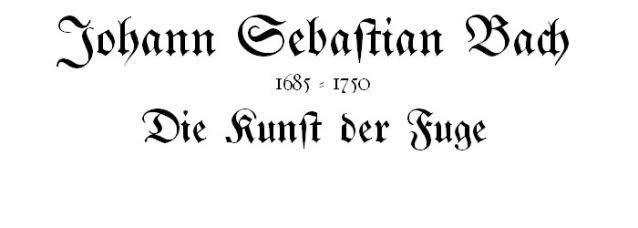
Johann Sebastian Bach
da darfst du nicht so dünnhäutig sein. das macht doch spaß, das alles aus zu probieren, wenn du schon selber nicht draufgekommen bist. ich glaube ich muß gleich mal mein titel einer reger broschüre reinlegen, so als beispiel für zeitgemäße, emotionale typo, nun gut das ist ein bisschen später, 1920 rum hat der gelebt und komponiert und miles davis (in blue note records-stil) war ab 1948 aktiv (die Franklin gabs schon ab 1920) miles davis geht aber auch in bodoni (warum nicht) usw. so sehe ich das. und bach: glenn gould, loussier oder die messe? da kann viel gut sein.
Die Breitkopf-Fraktur ist eine in Deutschland zur Zeit des Barock entstandene Fraktur.
Entworfen wurde sie etwa 1750 von Johann Gottlob Immanuel Breitkopf. Sie ist weniger verziert als andere Schriften des Barock und gilt als schönste und meistverwendete Fraktur Ihrer Zeit.
Da schließt sich der Kreis immerhin. Das Verlagshaus Breitkopf oder heute Breitkopf und Härtel sind schließlich die bedeutensten Musikverleger Deutschlands und haben auch die erste Gesamtausgabe der Werke Bachs herausgegeben.
Bretikopf war nebenbei bemerkt auch ein kleiner Tüftler und hat analog zu Gutenberg den Notendruck mit beweglichen Typen entwickelt.